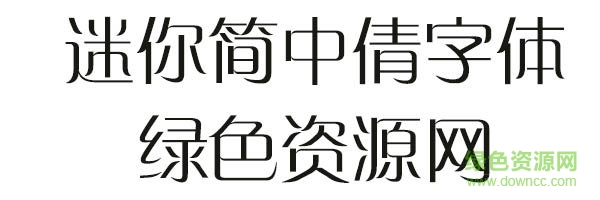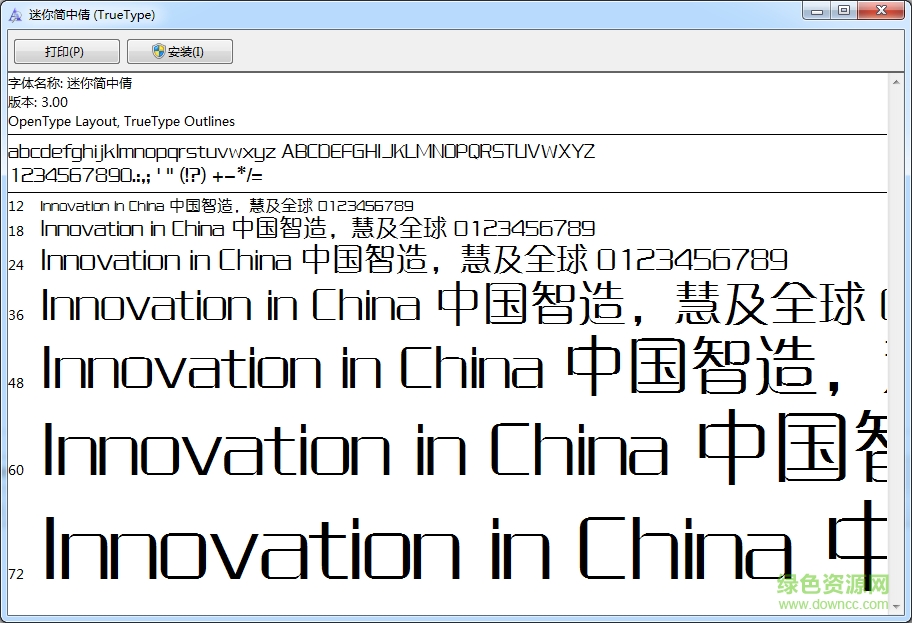
迷你簡中倩字體是一款非常優(yōu)雅的迷你字體,字體非常的正楷,筆畫纖細(xì)優(yōu)雅,簡潔大方,支持中文、英文和阿拉伯?dāng)?shù)字,非常的實用,歡迎喜愛此字體的用戶到綠色資源網(wǎng)下載使用!
迷你簡中倩體是迷你字庫中的一中簡體中文字體,可應(yīng)用于正文標(biāo)題、藝術(shù)創(chuàng)作、平面廣告、雜志報刊等領(lǐng)域。